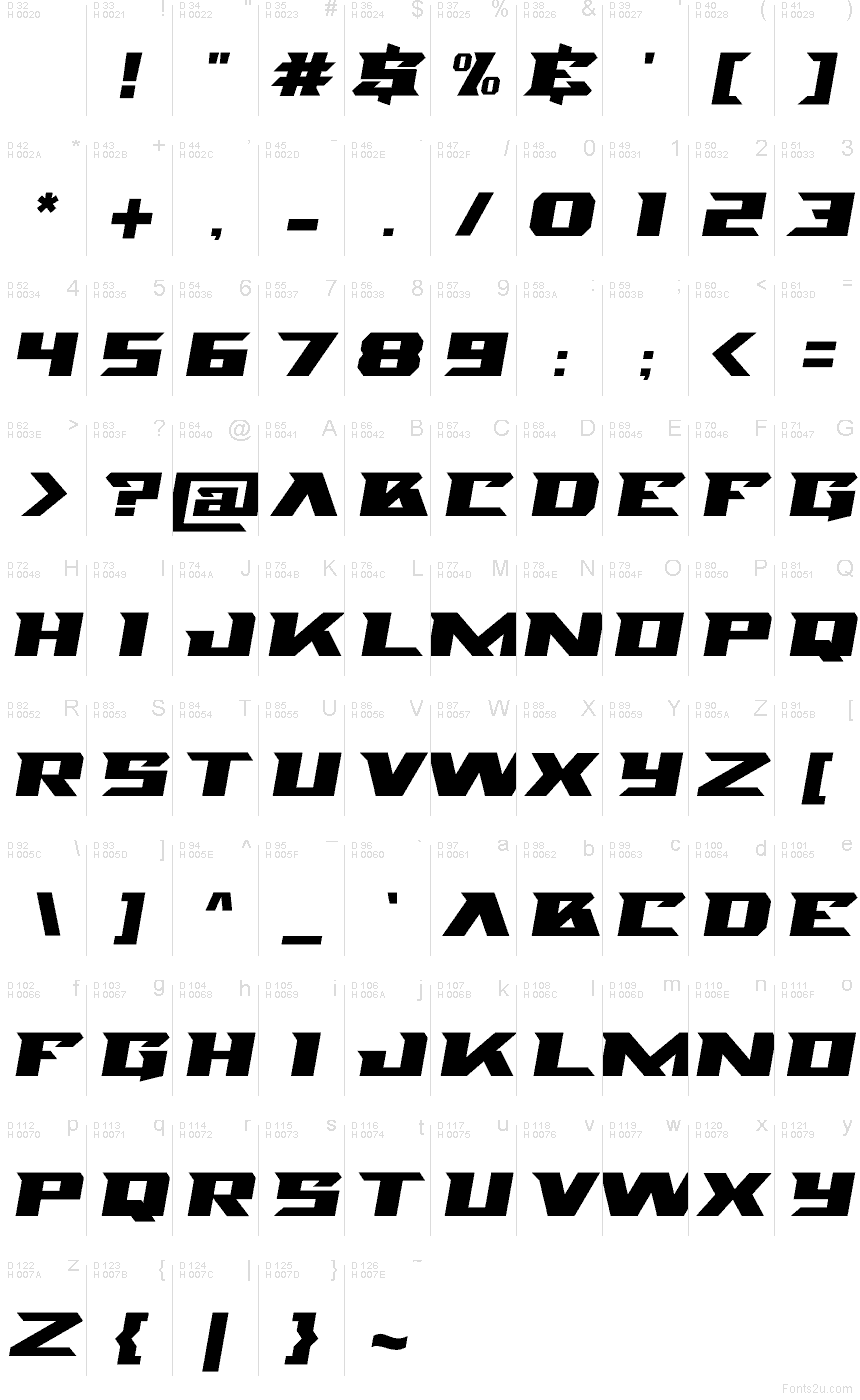
Blade Knight Italic de Maknastudio es una tipografía de rótulo futurista y gratuita, construida a partir de mayúsculas anchas, muy juntas y de corte afilado. La fuerte inclinación y los espacios en forma de cuña transmiten una sensación rápida y mecánica en las letras.
Su estilo de ciencia ficción es ideal para portadas de videojuegos y carteles de deportes de acción, donde los trazos diagonales repetidos sugieren blindaje, maquinaria y velocidad. Su mayor potencial se encuentra en los logotipos, con siluetas compactas que convierten un nombre en un emblema para merchandising de esports o imagen de marca de juegos arcade.